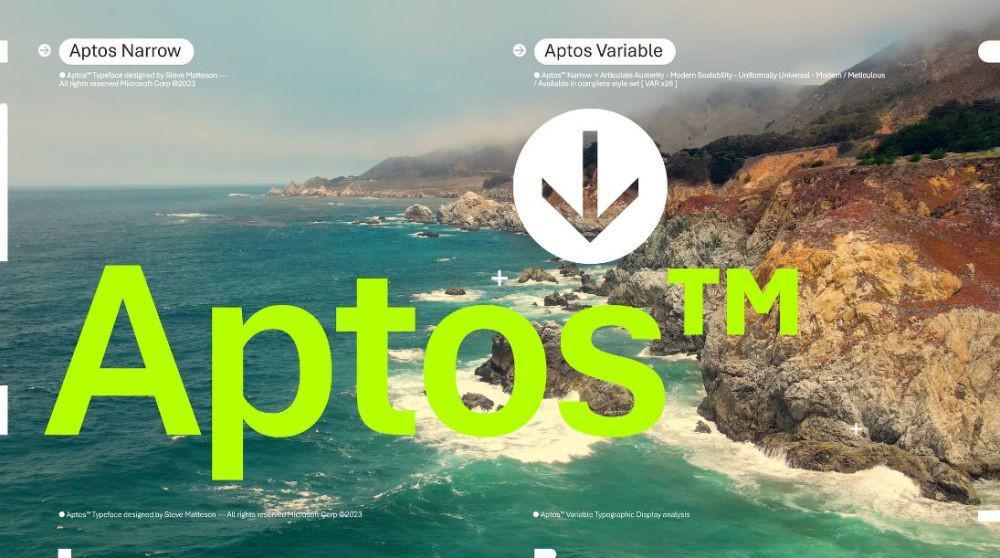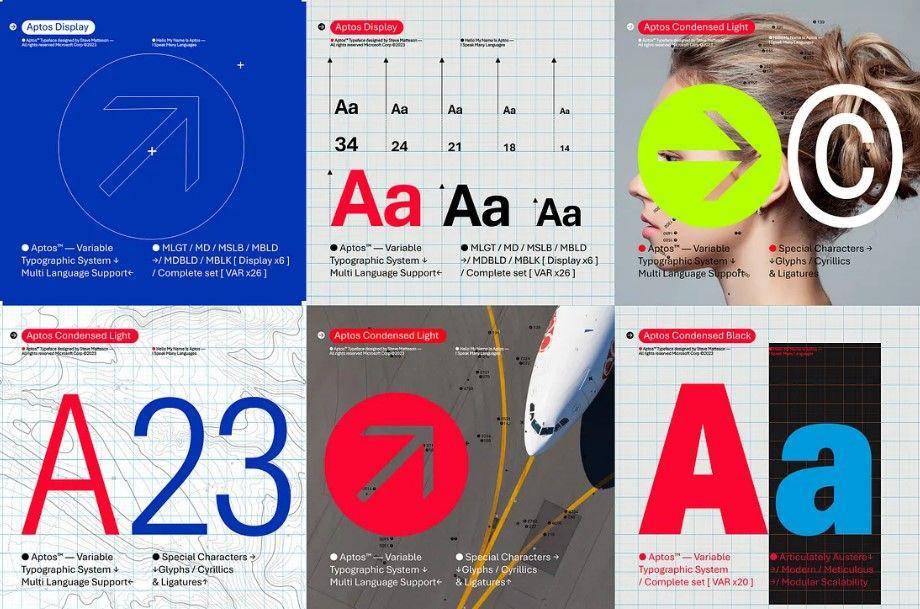
"Hari ini, kami memulai fase terakhir dari perubahan besar ini di mana Aptos akan mulai muncul sebagai font default baru di Word, Outlook, PowerPoint, dan Excel untuk ratusan juta pengguna," tulis Si Daniels, Manajer Produk Utama di Microsoft, dalam sebuah unggahan di blog Microsoft Design.
Microsoft Kenalkan Font Default Baru, akan Gantikan Calibri!
Microsoft secara resmi telah mengumumkan kehadiran sebuah font 'default' terbaru mereka untuk layanan produk Microsoft. Font tersebut diberi nama 'Aptos' dan akan menggantikan fungsi font default 'Calibri' yang sudah lama ada pada produk Microsoft.
'Aptos' akan gantikan 'Calibri' sebagai font utama
ilustrasi Windows (unsplash.com/Windows) Calibri telah menemani pengguna Microsoft sejak lama. Tepatnya sejak ditetapkan sebagai font 'default' di Microsoft Office pada tahun 2007 atau sudah 15 tahun silam. Dengan hadirnya 'Aptos', posisi 'Calibri' sebagai font 'default' akan dipensiunkan.
Dalam lanjutan unggahannya Daniels mengungkapkan bahwa meski digantikan dengan Aptos, Calibri masih akan tetap ada di Microsoft 365. Calibri akan disematkan di menu font paling atas bersama dengan font Times New Roman dan Arial. Pada akhirnya, Daniels mengungkapkan bahwa font adalah preferensi masing-masing pengguna. Pengguna dapat memilih font favorit mereka meski sudah ada Aptos sebagai font default di Microsoft.
Mengenal font 'Aptos'
font Aptos (dok. Microsoft Blog) Sejatinya kabar mengenai pengganti 'Calibri' ini bukan berita baru. Microsoft sendiri sudah mulai mencari pengganti Calibri sejak beberapa tahun terakhir. Pada 2021 silam, Microsoft mengumumkan lima kandidat sebagai pengganti Calibri, yaitu Tenorite, Bierstadt, Skeena, Seaford, dan Grandview Font.
Aptos sendiri merupakan versi final dari font "Bierstadt" yang sudah melalui serangkaian revisi dan feedback pengguna. Aptos dibuat oleh desainer huruf terkemuka Steve Matteson dan merupakan huruf Sans Serif bergaya kontemporer, mirip tipografi Swiss abad ke-20. Font ini juga mengusung kotak melingkar halus di dalam kontur huruf. Ini memungkinkan keterbacaan yang lebih tinggi, terutama pada ukuran huruf yang kecil.
Aptos bakal digelontorkan secara bertahap dalam beberapa bulan ke depan. Sebagai font default, tentu Aptos akan bisa digunakan semua pengguna di produk Microsoft. Kita nantikan saja kehadirannya.